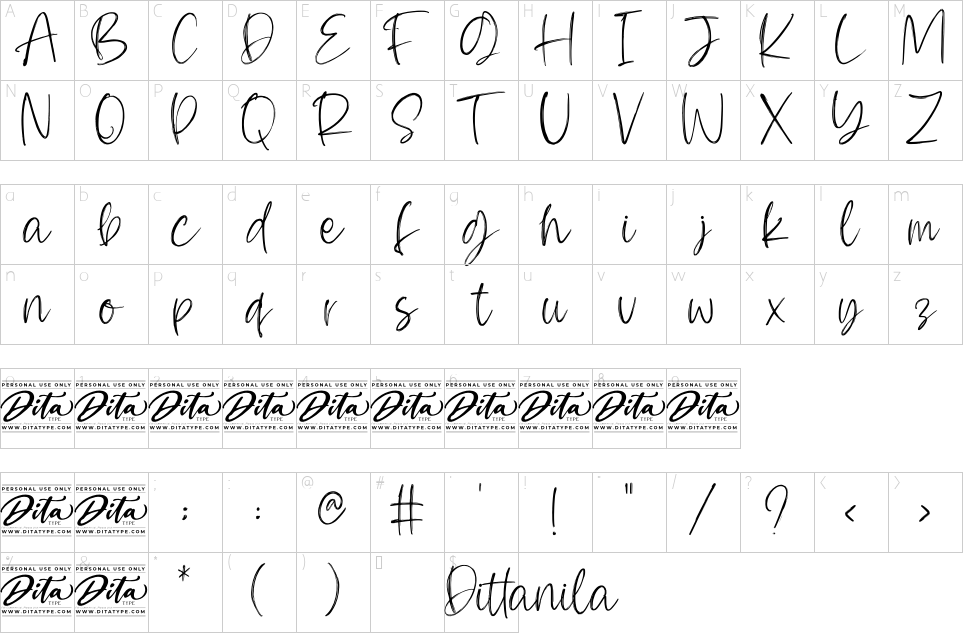
A Dittanila é uma elegante e versátil fonte que oferece um tom suave e fluido para textos digitais. Criada pela designer desconhecida Dita Type, esta fonte foi projetada com precisão e cuidado, resultando em linhas finas e espaçadas de forma idealizada. Ideal tanto para uso personalizado quanto para aplicativos profissionais, a Dittanila é uma escolha inteligente para designers gráficos. Com seu design minimalista e sua capacidade de adicionar um toque sofisticado aos documentos digitais, a fonte gratuita Dittanila é um recurso valioso para qualquer designer buscando uma fonte estilosa e fácil de usar em suas criações. Desde o início do ano, mais de duas mil pessoas já baixaram esta fonte, demonstrando sua adequação para um amplo espectro de usos, desde texturas simples até designs digitais avançados. Se você está procurando por uma fonte estilosa e versátil que não compromete seu design, a Dittanila pode ser o complemento perfeito para suas necessidades.